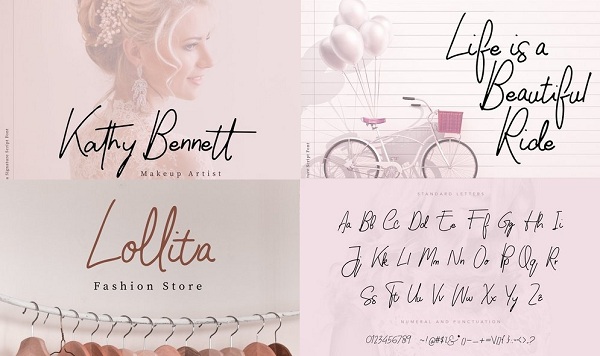
دانلود رایگان فونت هنری Molita Signature
دانلود رایگان فونت انگلیسی هنری Molita Signature
از این فونت انگلیسی زیبا و رایگان می توانید برای طراحی های مختلف و درست کردن امضاء شخصی و تجاری استفاده نمایید.حجم دانلود این فونت بسیار پایین می باشد و به می توانید به صورت کاملا رایگان از جی اف ایکس دانلود دریافت نمایید.